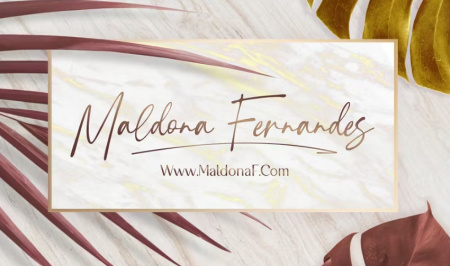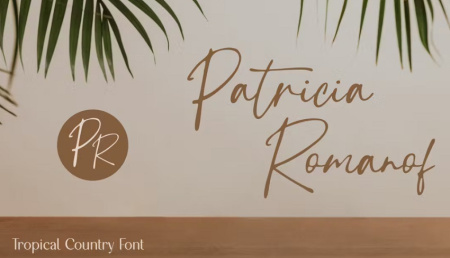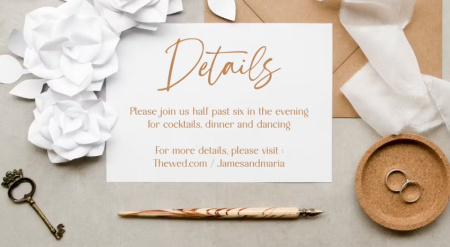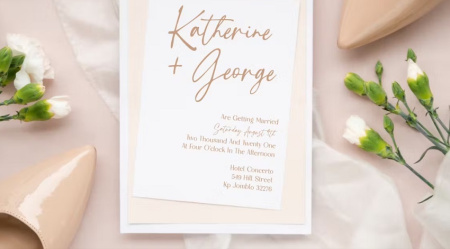
فونت انگلیسی Tropical Country
دانلود فونت انگلیسی Tropical Country یک فونت دست نوشته، این فونت برای برندسازی، دعوت نامه، لوازم التحریر، طرح های عروسی، پست های رسانه های اجتماعی، تبلیغات، بسته بندی محصول، طرح های محصول، برچسب، عکاسی، واترمارک، رویدادهای خاص و موارد دیگر عالی است.
✅ نام فونت انگلیسی: Tropical Country
✅ حروف بزرگ و کوچک
✅ اعداد و نقطه گذاری
✅ PUA کدگذاری شده است
✅ پشتیبانی چند زبانه